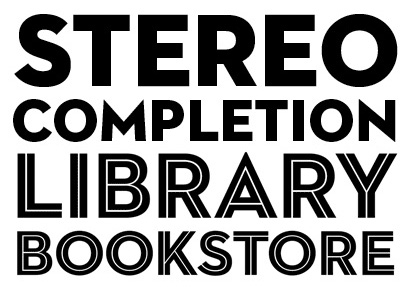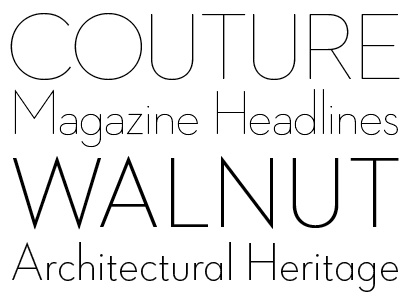
Neutraface No. 2 (House Industries)
Ja, das wird die Retroisten überzeugen, die bislang mit der Neutraface 1 ihre Probleme hatten . Aufjedenfall wird die Neutraface Familie jetzt vielseitiger einsetzbar. Angriff auf die Gotham in ihrer Popularität? Stephen Coles sprach ja polemisch von einer "Attack on Futura". Ok, so weit ist es noch nicht.